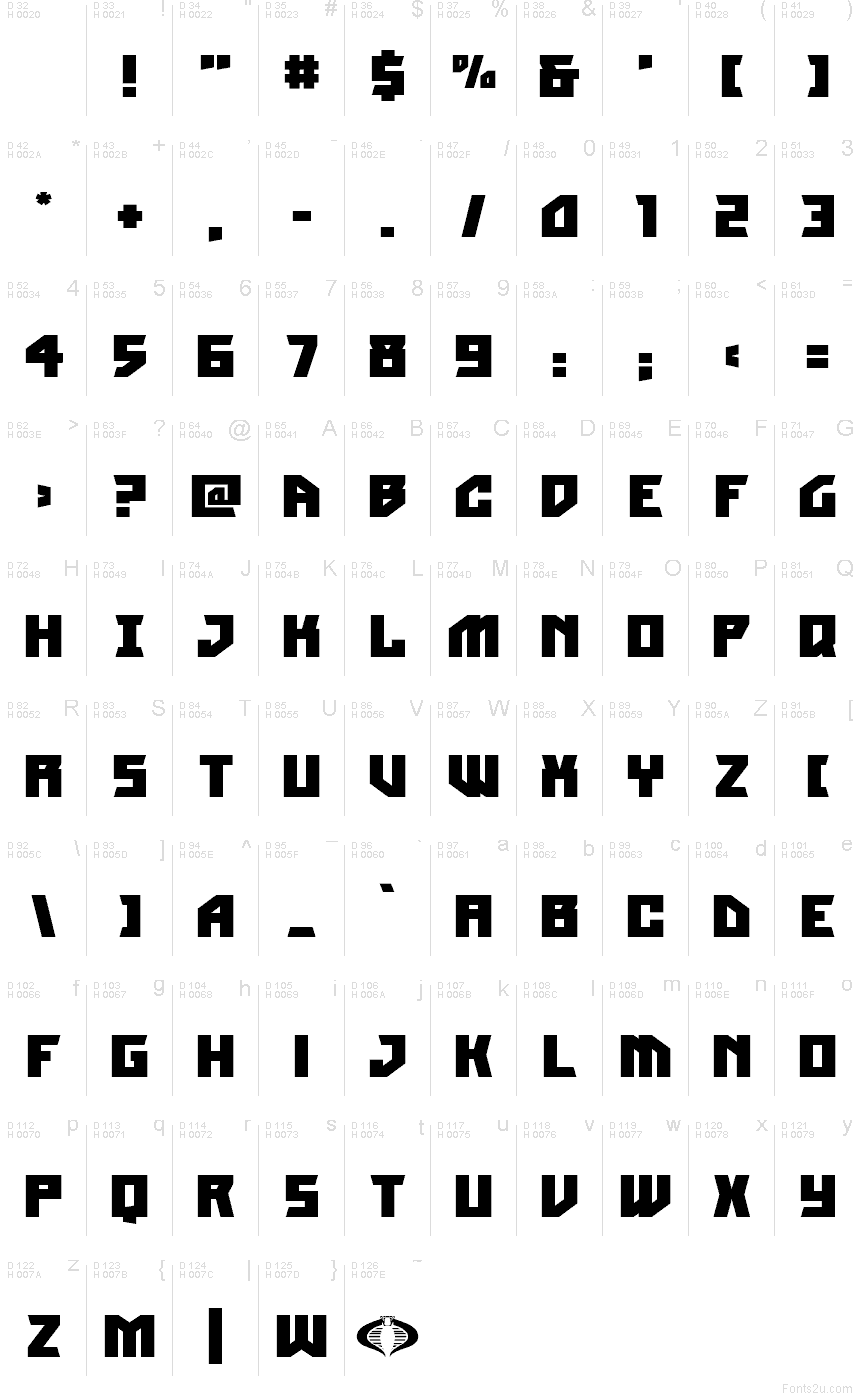
Omni-cobra Straight Wide
Omni-Cobra Straight Wide de Iconian Fonts es una tipografía techno display gratuita que destaca por sus cortes verticales afilados, sus contadores cuadrados y una construcción amplia y segmentada. Las letras parecen ensambladas a partir de barras rectas y diagonales recortadas, lo que otorga a esta familia un ritmo rígido y codificado.
Omni-Cobra Straight Wide funciona muy bien en pósteres de ciencia ficción, títulos de videojuegos, logotipos, portadas de álbumes y flyers de eventos, ya que su estructura angular transmite un marcado tono digital sin necesidad de adornos adicionales. Esta fuente gratuita también es ideal para etiquetas futuristas y titulares, cuando buscas que las propias letras aporten todo el impacto visual.